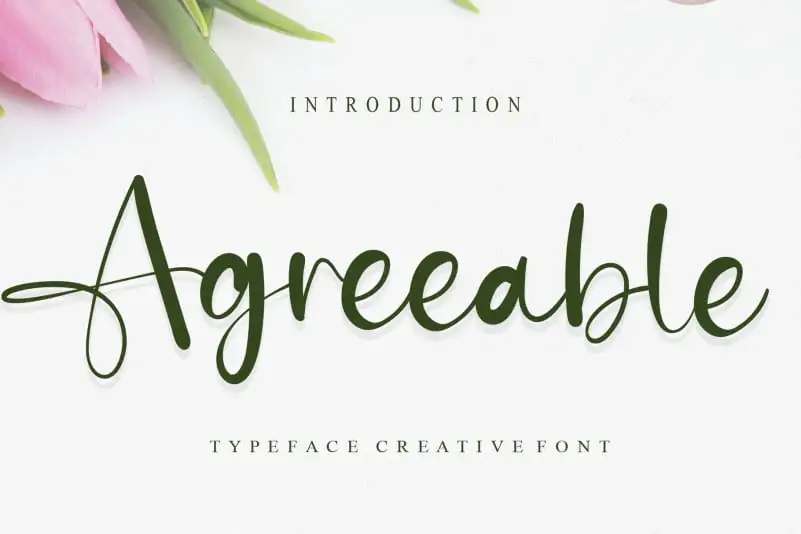
Agreeable Script Font – Fonte Grátis
Agreeable Script Font
A Agreável Script Font é uma grata surpresa para os designers que buscam uma caligrafia única e elegante. Ela oferece uma experiência visual única, com linhas fluidas e detalhes cuidadosamente concebidos pelo designer creativellert. Essa fonte não apenas ilumina seu trabalho de design mas também torna-o distinto e memorável. Com sua propriedade especial e sofisticada, a Agreável Script é perfeita para criar mensagens que chamam atenção em cartazes, logotipos ou qualquer outro projeto visual. Ela combina harmoniosamente com várias estilos de fontes e cores, oferecendo uma escolha variada e versátil, adequada tanto para projetos profissionais quanto pessoais. A Agreável Script é a escolha perfeita para quem busca uma caligrafia que seja não apenas bonita e elegante, mas também uma ferramenta poderosa de expressão visual.